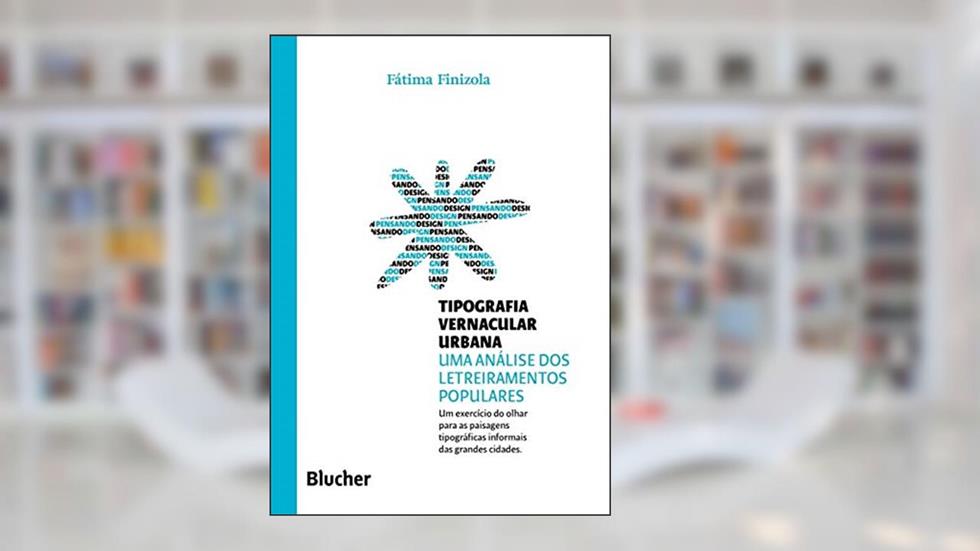
Tipografia Vernacular Urbana: uma Análise dos Letreiramentos Populares, do autor Fátima Finizola
Tipografia Vernacular Urbana
Uma Análise dos Letreiramentos Populares
Fátima Finizola
A cidade respira, e em sua respiração, notas e cores dançam à luz do sol. Tipografia Vernacular Urbana: uma Análise dos Letreiramentos Populares de Fátima Finizola vai muito além de um simples estudo sobre letras e imagens; é uma imersão no pulsar da vida urbana, onde cada letreiro é um grito silencioso de identidade e resistência. ✨️
Adentrar as páginas dessa obra é como passear por ruas de uma metrópole que se revela aos poucos. Você não apenas observa, mas sente a história pulsante em cada letra desenhada à mão, em cada painel colorido. Finizola desmistifica o universo da tipografia popular, revelando um rico mosaico que traz à tona a cultura e as vivências de uma sociedade multifacetada. A obra é uma ode ao que geralmente passa despercebido, ao que a maioria ignora. 🚧
Nesse contexto, os letreiramentos populares não são meros anúncios; eles são narrativas visuais, expressões do cotidiano que trazem à tona a luta, os sonhos e o modo de vida das comunidades urbanas. A autora nos provoca a enxergar a beleza na simplicidade e na crueza de cada traço - uma tipografia que fala, grita e, muitas vezes, se entristece. Os comentários de leitores que mergulharam nesses estudos revelam um sentimento comum: a obra desperta um olhar renovado para o urbano, uma nova apreciação pela arte que se manifesta em cada esquina. 🌈
E aqui reside a grande magia de Fátima Finizola: ao fazer essa análise profunda dos letreiramentos, ela não se limita à estética, mas aborda questões sociais, políticas e culturais que permeiam cada canto da cidade. A conexão entre as letras e a identidade de um povo revela-se crucial, e sua análise nos convida a uma reflexão sobre a representatividade e a autenticidade no espaço urbano. Não à toa, muitos leitores relatam saírem transformados dessa experiência literária, mais conscientes e sensíveis ao que os cerca.
Você pode se perguntar: "Por que isso importa?" A resposta é clara. Em um mundo que caminha para a homogeneização, a valorização do vernacular se torna um bastião da diversidade cultural. Cada letreiro é uma história, uma memória, uma fragmentação de uma identidade que se resiste a se apagar. A obra de Finizola se transforma em um manifesto, um chamado à ação para que não apenas apreciemos, mas também lutemos pela preservação da singularidade e autenticidade que habitam as cidades.
Para aqueles que têm olhos para ver, Tipografia Vernacular Urbana não é apenas uma leitura, mas um convite à revolução estética e cultural. O seu coração vai acelerar ao descobrir que cada letra, cada cor, é uma janela para o ser humano que a criou, para a história não contada que se desenha em letras e tintas. É um verdadeiro cartão de visita da alma coletiva, que nos ensina a respeitar, valorizar e, acima de tudo, sentir as histórias que se escondem nas sombras do cotidiano. ❤️
Se você ainda não mergulhou nesse universo fascinante, está perdendo a chance de silenciar o ruído do cotidiano e escutar as vozes que clamam por atenção. São essas vozes que compõem a rica tapeçaria da cultura urbana, e Fátima Finizola é a guia perfeita para essa jornada única. 🍀
📖 Tipografia Vernacular Urbana: uma Análise dos Letreiramentos Populares
✍ by Fátima Finizola